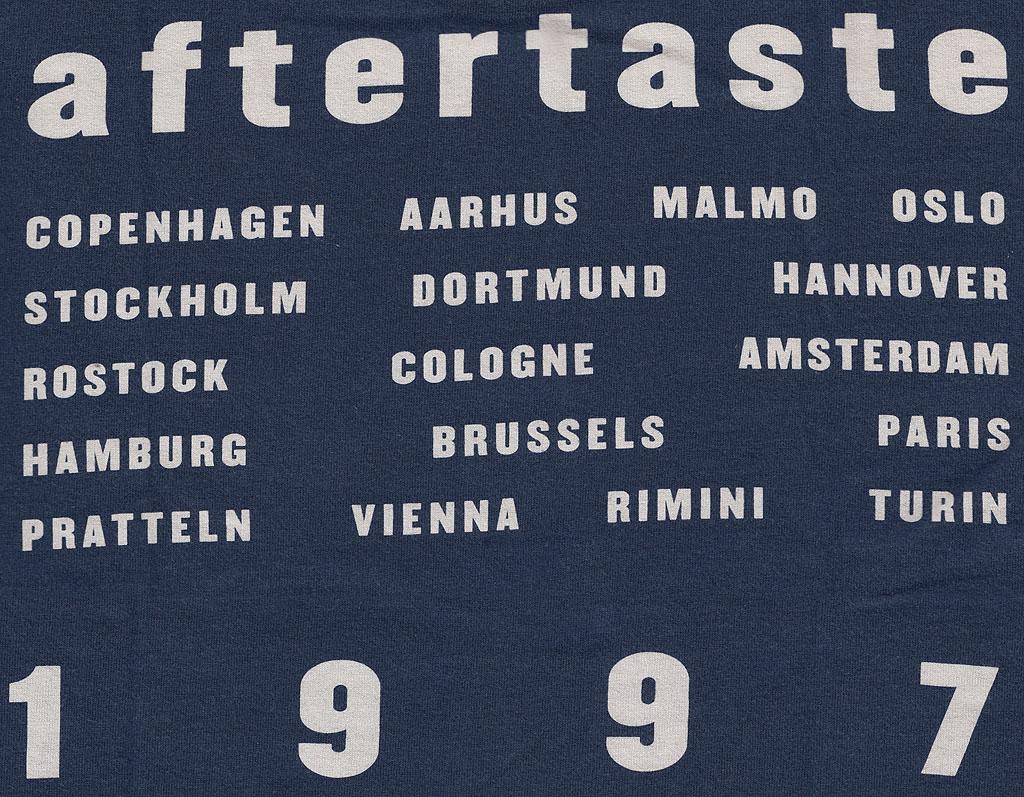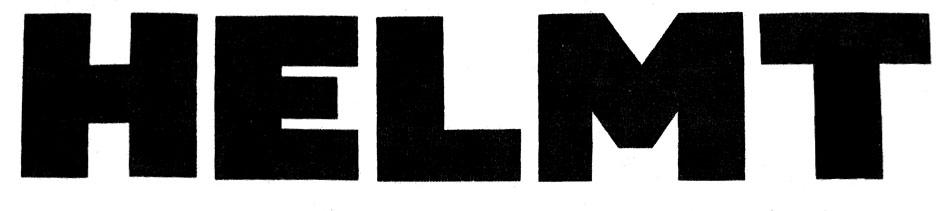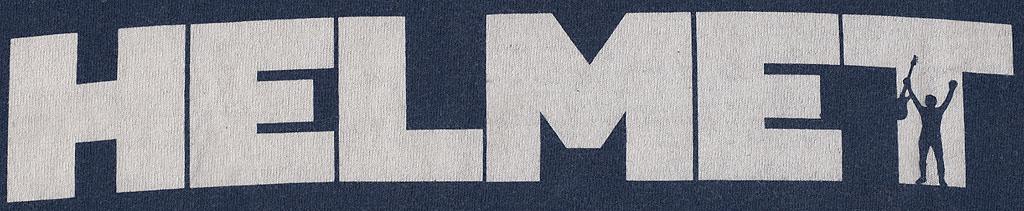
Serifenloses der 90er-Jahre
Ich hab' mal wieder ein T-Shirt, das auf den zweiten Blick Schrifträtsel aufgibt.
Hab' natürlich schon die üblichen Erkennungsquellen gecheckt, so richtig eindeutig war keins.
Das Hemd ist aus dem Jahr 1997.
Keiner eine Idee? Sehe gerade, es fehlt ja auch Frage. :-)
Erkennt jemand die hier verwendeten Schrift(en)?
die bei »aftertaste« hat zumindest einige ähnlichkeit mit der garage gothic.
details – besonder beim »a« sind aber anders. der charakter passt aber ganz gut.
Ja, ich glaub das ist sie. Am "Helmet", speziell am M, ist wahrscheinlich geschraubt worden, sonst könnte da fast der Heavyweight-Schnitt passen.